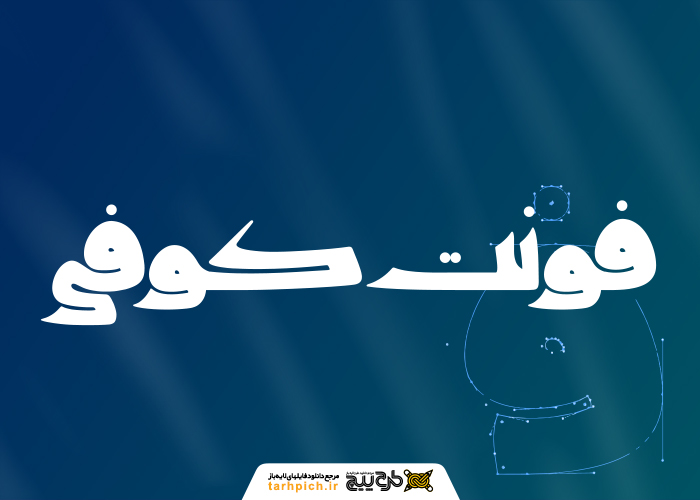
فونت کوفی
فونت فارسی  کوفی با طرحی به نظیری که دارد در خیلی از طرح‌ها قایل استفاده است. همچنین فونت کوفی مورد پسند اکثر افراد قرار می‌گیرد. برای دانلود فونت کوفی ابتدا در سایت نیز ثبت نام کنید. سپس پس از ثبت نام می‌توانید فونت ایران نستعلیق را نیز دانلود کنید.در فونت کوفی از فرمت TTF استفاده شده که قابلیت اجرا شدن در تمامی نرم افزار ها را دارد.طراحان و گرافیست ها می توانند از این نوع فونت زیبا در طراحی های خود استفاده کنند.فونت کوفی در دسته بندی فونت های فارسی قرار دارد. فونت کوفی فرمی قدیمی و مذهبی دارند و شما می توانید برای طراحی پوستر و جلد کتاب  های مذهبی از این نوع فونت استفاده کنید .اگر به دنبال طرح های گرافیکی هستید روی لینک کلیک کنید.